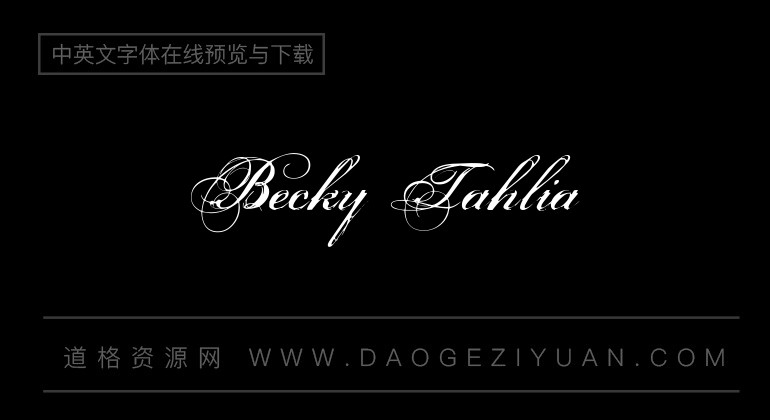
Becky Tahlia 是一款细腻而精致的英文字体,它的字形有着优雅的曲线,并且具有浓郁的人文气息。它的字体结构清晰,字体的笔画让它看起来更加立体,而且易于阅读。Becky Tahlia字体的细节表现出美感,它的细节更加清晰,看起来更加优美。它的笔画更加精致,而且在空间构图上也更加丰富,能够更好的表达文字的表达力。内容介绍
Becky Tahlia是一款非常不错的手写艺术字体,具有很好的视觉感,适合于文化类的宣传设计、商业类品牌的广告和产品包装设计以及个性化文字排版等较多场景。